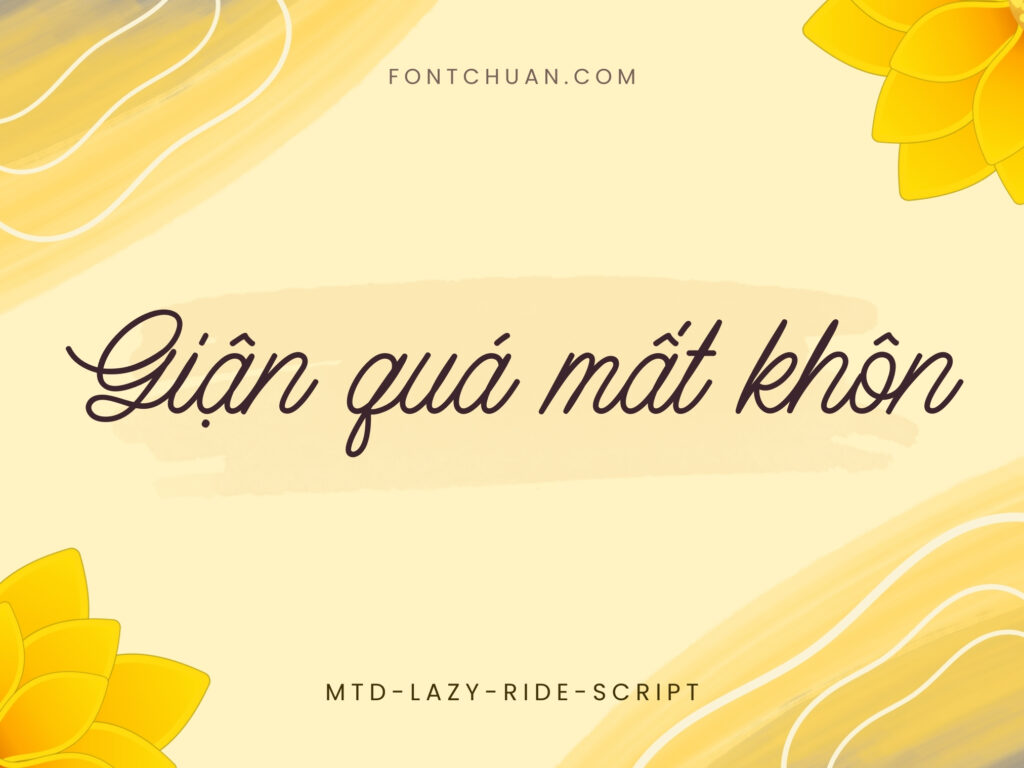
Font MTD Lazy Ride Script Việt Hóa
Tác giả Font: Hendra Pratama
Font MTD Lazy Ride Script là một phông chữ viết tay thanh lịch, được thiết kế bởi Hendra Pratama và đã được Việt hóa bởi Mộc Hạ. Font này hỗ trợ đầy đủ tiếng Việt cùng hơn 90 ngôn ngữ khác, giúp mở rộng khả năng ứng dụng trong các thiết kế đa ngôn ngữ. Với hơn 670 ký tự và các tính năng OpenType phong phú, Lazy Ride Script mang đến sự linh hoạt và sáng tạo cho người dùng.
MTD Lazy Ride Script nổi bật với các đường nét mềm mại và uyển chuyển, tạo cảm giác tự nhiên và thân thiện. Font rất phù hợp cho các thiết kế logo, tiêu đề, bao bì sản phẩm, thiệp mời và các ấn phẩm đòi hỏi sự tinh tế và nghệ thuật. Các ngành nghề phù hợp bao gồm quảng cáo, giáo dục, công nghệ, thiệp cưới và ảnh cưới. Font này cũng lý tưởng cho các sự kiện như Tết, Giáng sinh, Valentine và các lễ hội khác.